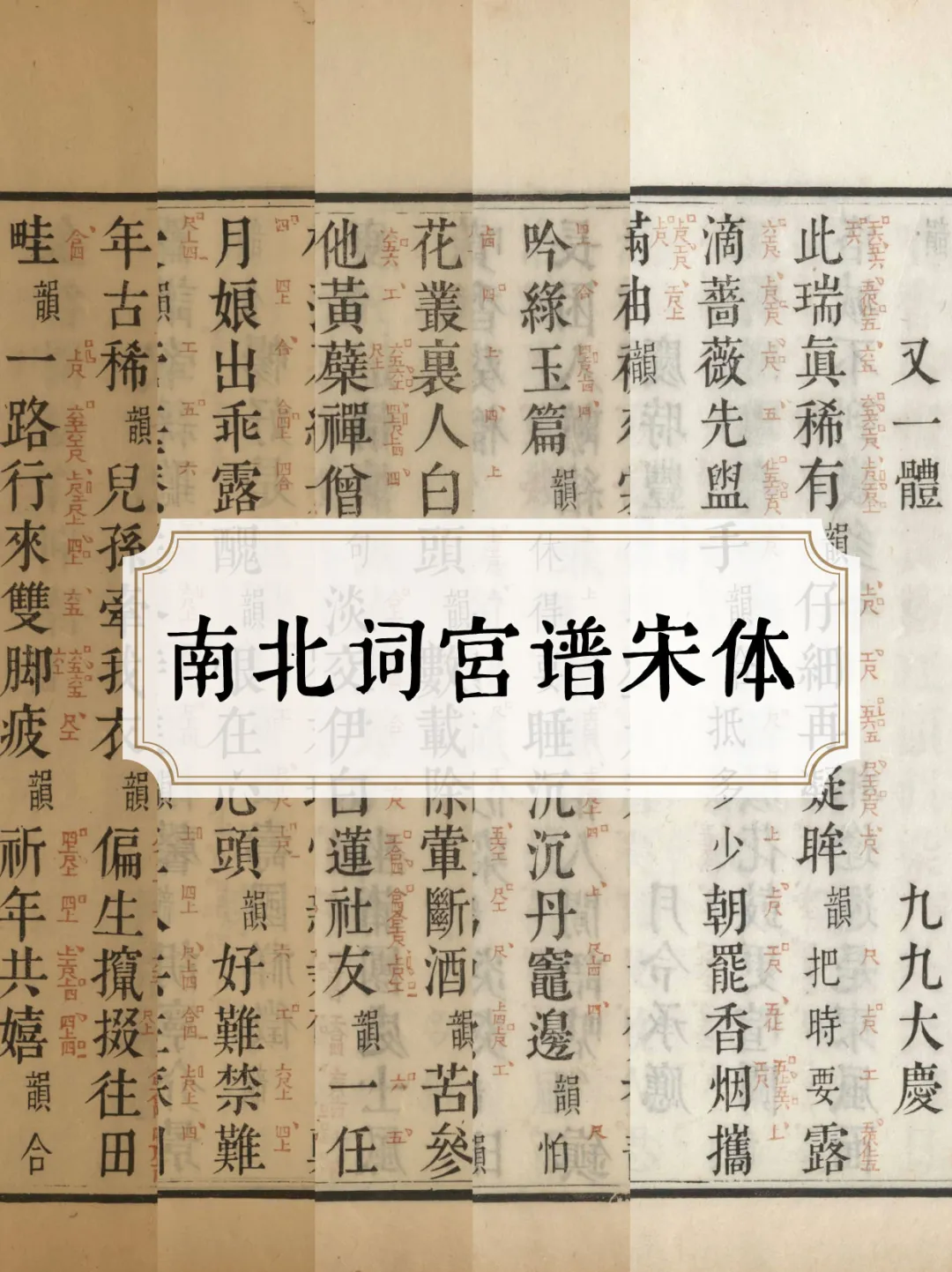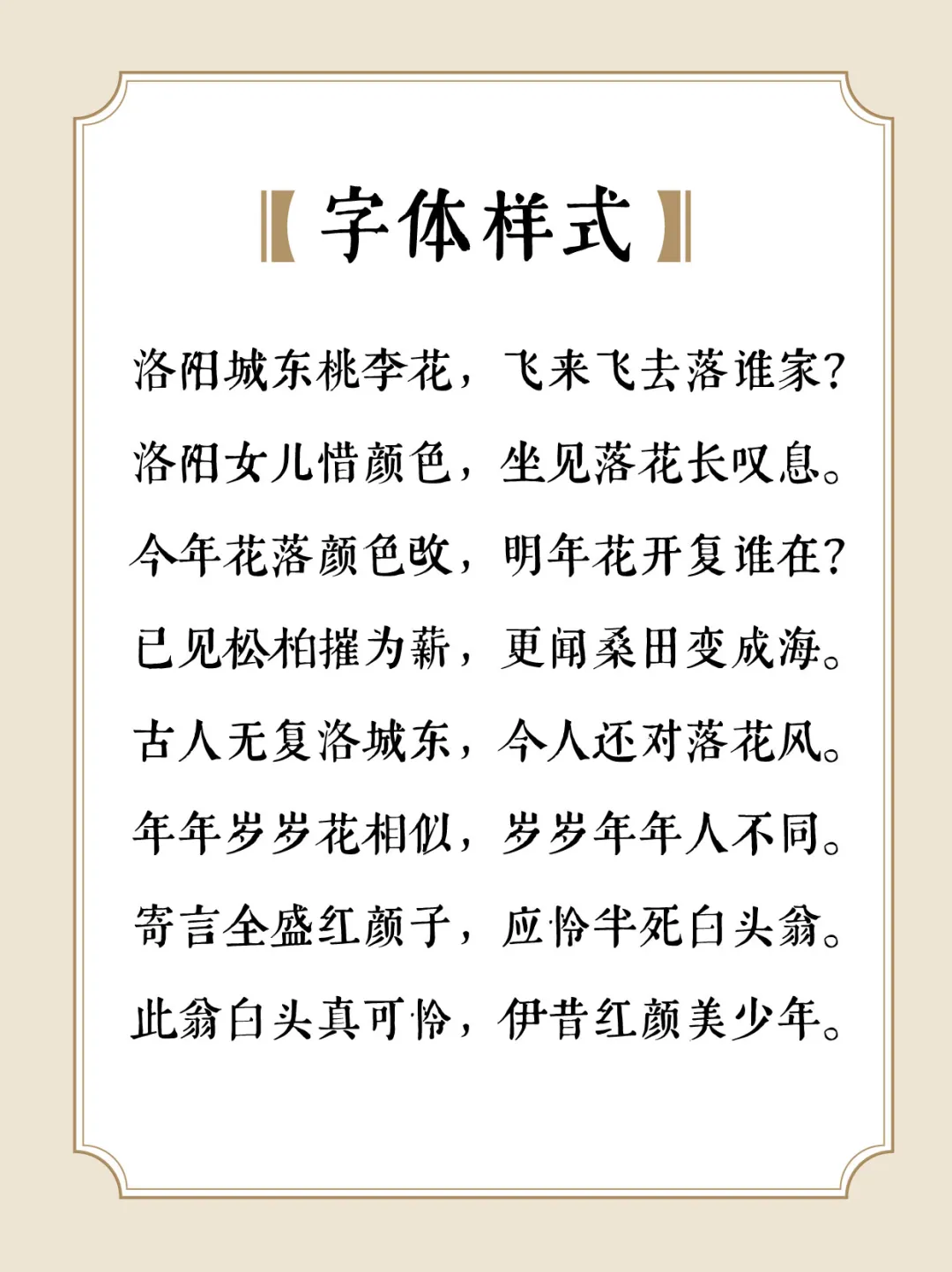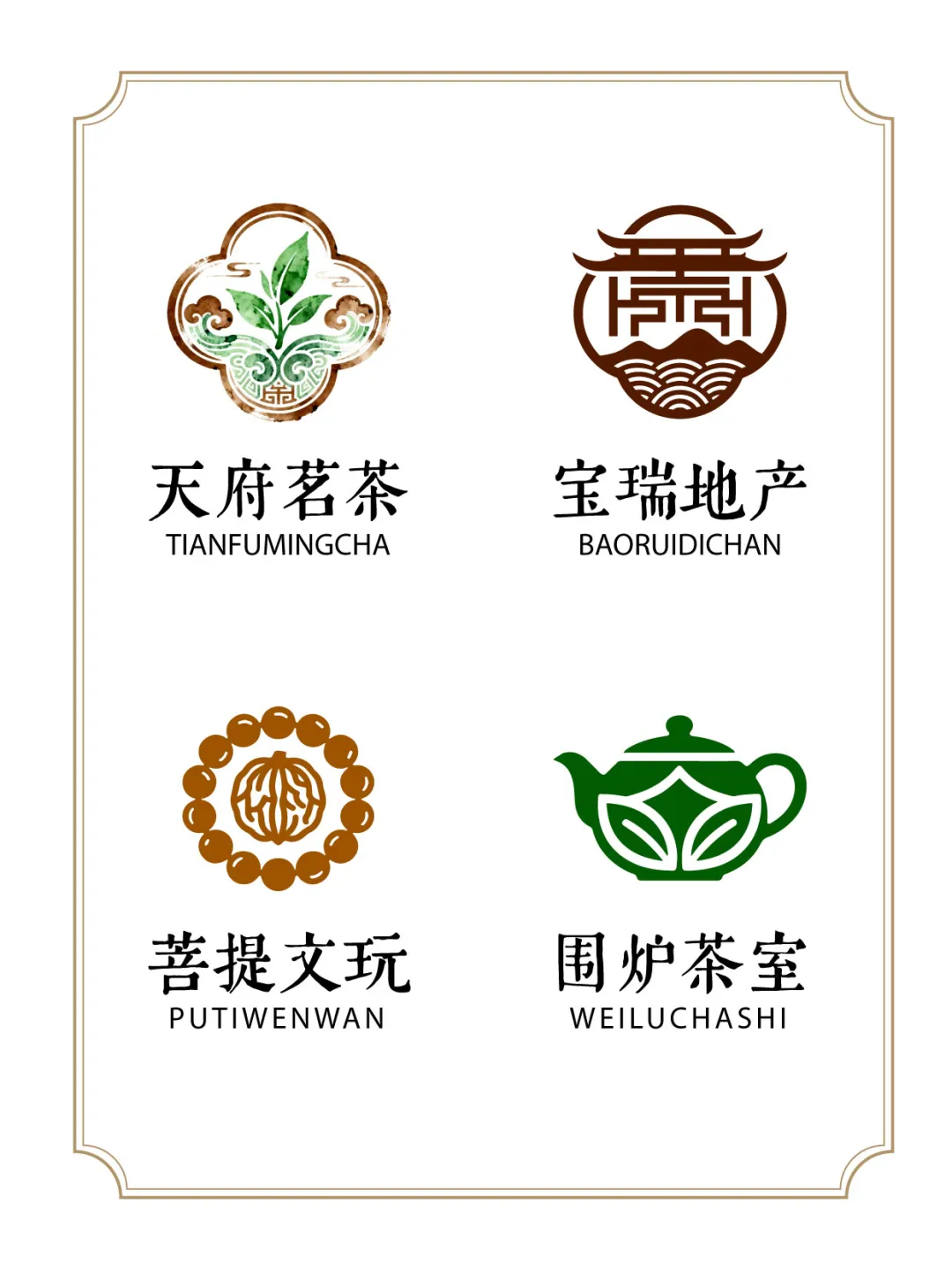
南北词宫谱宋体是由郑庆科(庆科字体)借助人工智能技术生成的一款免费商用中文字体,原型取自古籍《新定九宫大成南北词宫谱》。作者从中拆分出 30 余万个字符图像,再经人工筛选得到 5000 余个字符图像,在保持原本字型线条的情况下运用生成对抗网络(GAN)进行多次训练,最终输出了这款字库文件。
南北词宫谱宋体保留了原版古籍的古朴质感,又验证了新技术的可行性。支持国家标准 GB 2312 编码字符集、大五码字符集、Unicode 基本字符集,包含中文简体、中文繁体、拉丁字母、阿拉伯数字和各类标点,总计 21943 个字符;同时设有两个版本,一个是包含上述全部字符的完整版本,另一个是原版复刻版本,仅收录人工筛选出的 5716 个简繁体字符。适合需要古朴风格的设计场景,如国潮海报、传统节日、文化展览、书画雅集、非遗活动、茶酒香品等。